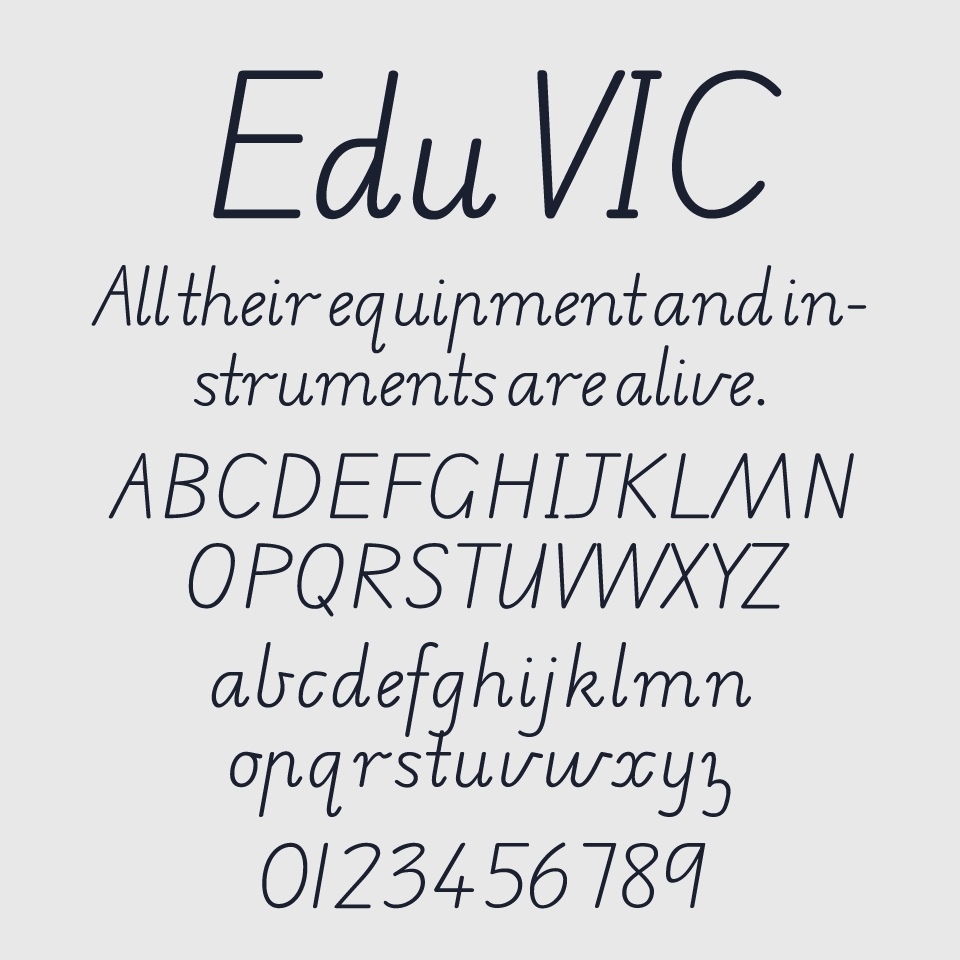
Edu VIC WA NT Handフォントは、大人っぽさのある手書き文字をベースにした繊細で実用的な筆記体フォントです。
細くてやわらかな曲線は、大人っぽさのある手書き文字で、まるで教科書や学習ノートに書かれた文字のようも見えるぐらい整っている文字です。読みやすく整理された字形は、書き取り練習やナチュラルな表現に向いています。